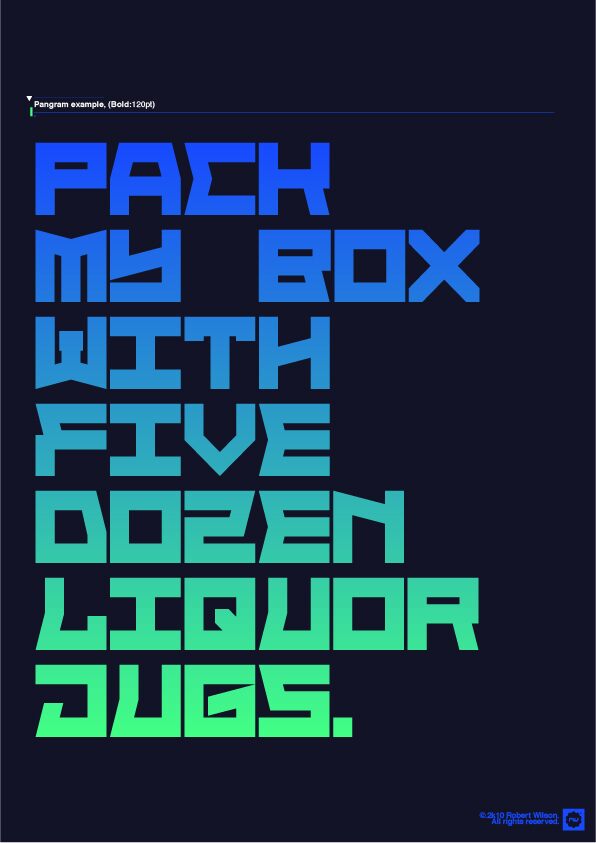
Block Face Bold ist eine kostenlose geometrische Techno-Schrift in Versalien von Robert Wilson, die auf breiten, rechteckigen Strichen und scharfen, kantigen Ausschnitten basiert. Die Buchstaben wirken industriell und präzisionsgefertigt; die geschnittenen Verbindungen und facettierten Öffnungen erzeugen einen harten, prägnanten Rhythmus.
Ihre wuchtige Silhouette sorgt für einen technisch-konstruierten Look bei Spieletiteln und Esports-Identitäten, während die gebrochene Geometrie ideal für Sci-Fi-Poster und Cover elektronischer Musik geeignet ist. Verwenden Sie diese kostenlose Schrift für Tech-Verpackungen oder Event-Beschilderungen, wenn das Design an gepanzerte Platten, digitale Hardware und retro-futuristische Maschinen erinnern soll.